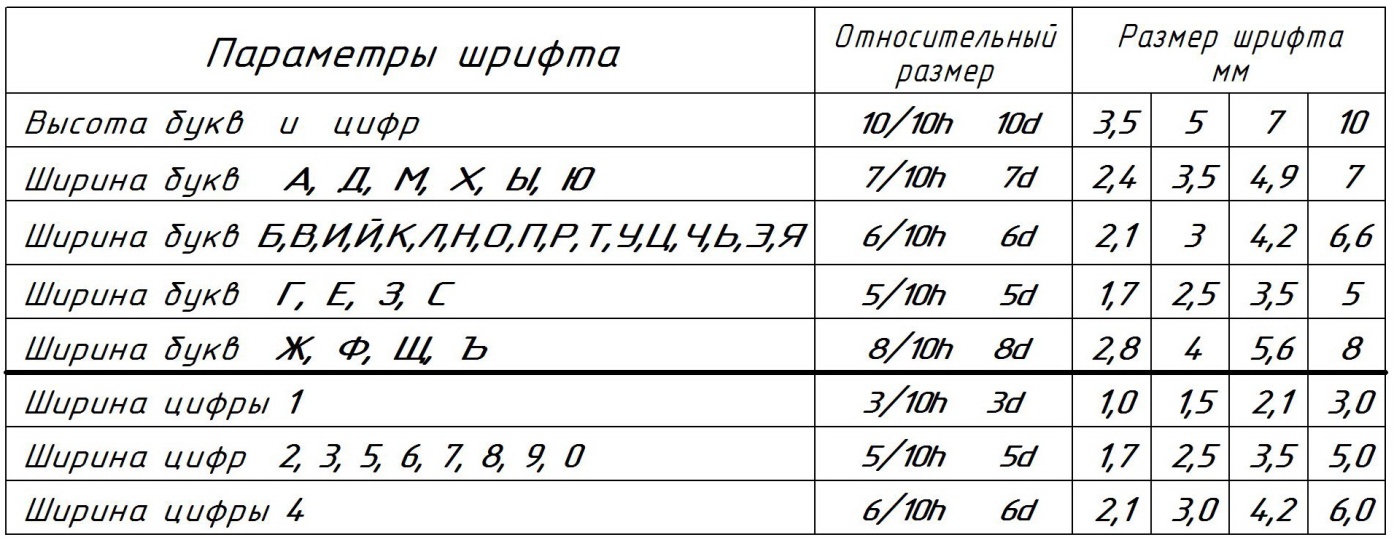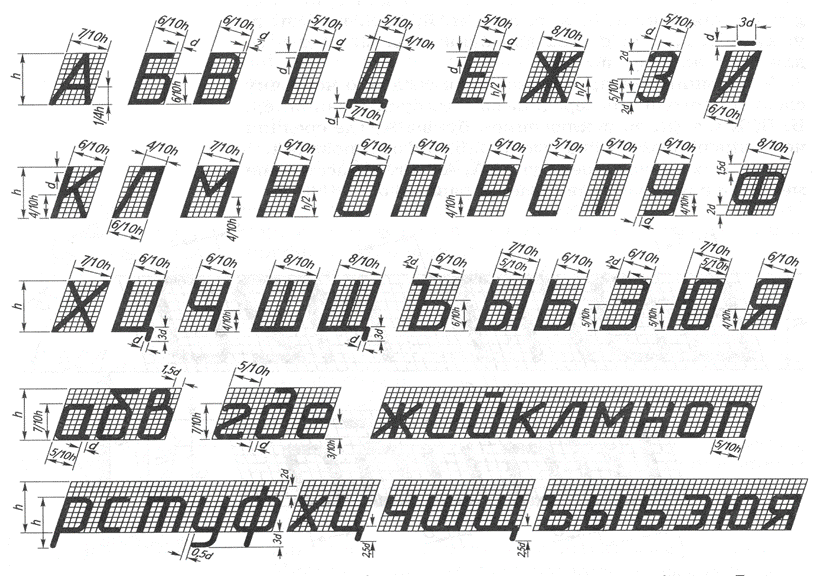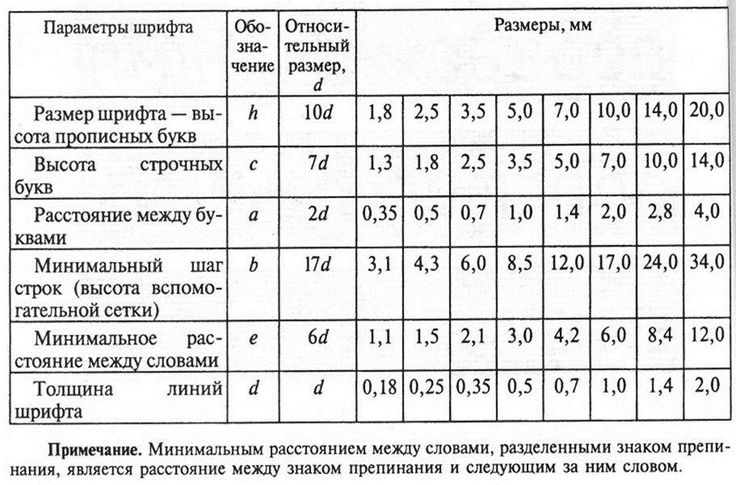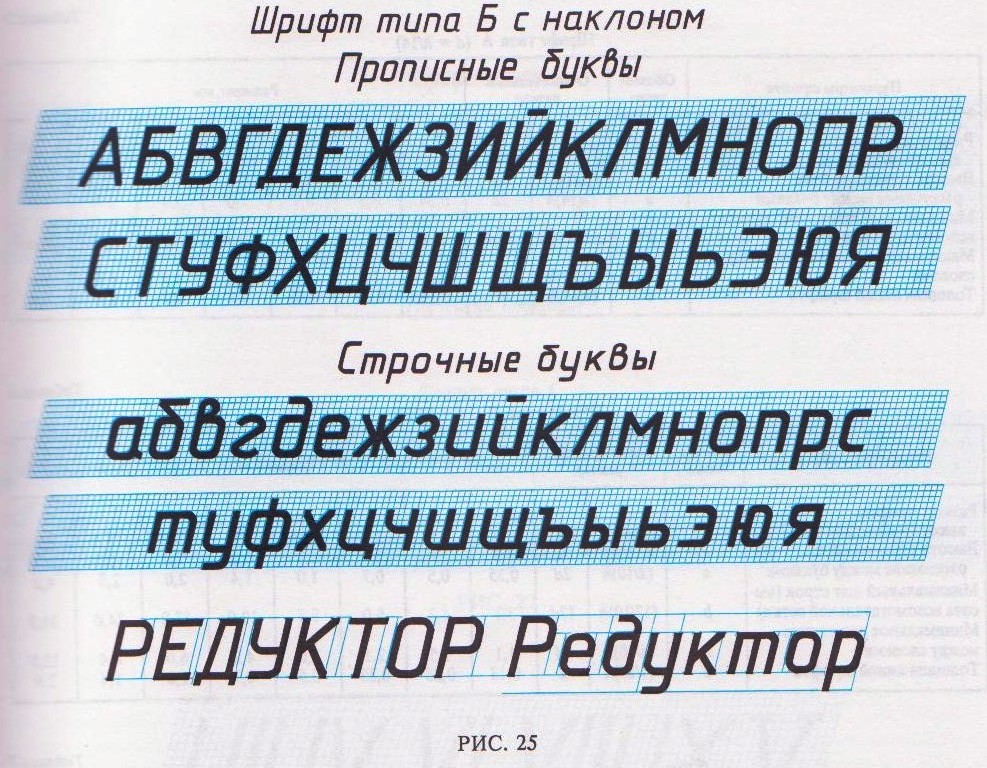
На чертежах и схемах кроме размерных чисел наносят различные надписи как в графах основной надписи (угловом штампе), так и на поле чертежа — надписи с обозначением изображений, а также надписи, относящиеся к отдельным элементам изображаемого изделия или здания. Надписи должны быть ясными и четкими.
Чертежные шрифты.
ГОСТ 2.304—81* устанавливает шрифты для надписей, наносимых на чертежах и технических документах всех отраслей промышленности и строительства. Чертежные шрифты характеризуются простотой конструкции букв, цифр и знаков. Для лучшего восприятия конструкции шрифта его построение показано на вспомогательной сетке (рис.1 а, б), шаг линий которой зависит от толщины линий шрифта. Наклон букв и цифр данного шрифта к основанию строки равен примерно 75°.
Рис.1. Чертежный шрифт с наклоном (тип Б): а — прописные буквы, б — строчные буквы, в — арабские цифры
Размер шрифта характеризуется высотой h прописных букв в миллиметрах (см таблицу).
Таблица Размеры букв и цифр чертежного шрифта типа Б по ГОСТ 2.304-81*
Параметры шрифта | Обозна- чение | Относительный размер | Размеры, мм |
Размер шрифта: — высота прописных букв — высота строчных букв | h с | (10/10)h 10d (7/10)h 7d | 2,5 3,5 5 7 10 14 20 1,8 2,5 3,5 5 7 10 14 |
Расстояние между буквами | а | (2/10)h 2d | 0,5 0,7 1 1,4 2 2,8 4 |
Минимальный шаг строк | b | (17/10)h 17 | 4,3 6 8,5 12 17 24 34 |
Минимальное расстояние между словами | е | (6/10)h 6d | 1,5 2,1 3 4,2 6 8,4 12 |
Толщина линий шрифта | d | (1/10)h d | 0,25 0,35 0,5 0,7 1 1,4 2 |
П р и м е ч а н и е: g -наибольшая ширина буквы, g=6/10h
Установлены следующие размеры шрифта: 2,5; 3,5; 5; 7; 10; 14; 20; 28; 40.
Параметры шрифта зависят от размера шрифта h или от толщины линии шрифта d, равной 1/10h (рис. 2, а).
Высота строчных букв с определяется из отношения их высоты (без отростков h) к размеру шрифта h и составляет с = 7/10h.
Ширина большинства прописных букв равна б/10h (6d). Ширина букв А, Д, М, X, Ы, Ю— 7/10h (7d), а букв Ж, Ф, Щ, Ъ — 8/10d (8d).
Ширина строчных букв и арабских цифр, кроме цифры 1, составляет 5/10h (5d). В 16 случаях конструкция строчных букв повторяет прописные.
Рис.2. Основные типы шрифта и параметры в конструкции букв:
а — шрифт с наклоном (тип Б), б — без наклона (тип Б), в — построение шрифта по вспомогательной сетке, г — построение шрифта с толщиной линий, равной 1/14 высоты прописных букв (тип А)
Скругленные участки прописных букв выполняют в пределах двух толщин (2d) линий шрифта.
Расстояние а между буквами, соседние линии которых не параллельны между собой (например, ГА, AT), может быть уменьшено наполовину, т.
е. на толщину d линии шрифта. Цифру 1 размещают на расстоянии от смежных цифр и букв, равном 2/10h. На рис. 1в дан вариант выполнения цифры 3.
Минимальным расстоянием между словами е, разделенными знаком препинания, является расстояние между знаком препинания и следующим за ним словом. Минимальный шаг строк b, или расстояние между основаниями строк, составляет 17/10h. Таким образом, величина промежутка между строками прописных букв должна быть не менее высоты строчных букв — 7/10h.
При выполнении надписей применяют также чертежный шрифт без наклона (рис. 2, б), имеющий те же размеры и параметры, что и шрифт с наклоном.
ГОСТ 2.304—81* устанавливает еще два чертежных шрифта — с наклоном и без наклона — таких же размеров, но другого типа (рис, 2, в, г), в которых толщина линии шрифта d составляет 1/14h.
Выполнение надписей.
Прежде чем приступить к выполнению надписи, надо хорошо изучить конструкцию букв и цифр шрифта, которым будет исполнена надпись.
При выполнении надписей между двумя параллельными линиями, проведенными на расстоянии, которое соответствует высоте прописных букв, посередине можно провести еще одну линию (рис, 3, а). В большинстве случаев в конструкции букв средние горизонтальные участки линий проводят выше середины высоты прописных букв и цифр. Надписи, заголовки могут состоять только из прописных (заглавных) букв или из прописных и строчных букв (рис. 3, б).
Рис.3. Параметры шрифта (тип Б) (а) и приемы выполнения надписей (б)
При выполнении надписи определяют место для нее и задаются размером шрифта. После этого, если надпись крупная, т. е. высота букв больше 7 мм, необходимо:
— на отведенном для надписи месте провести две параллельные линии на расстоянии, соответствующем высоте букв;
— от начала надписи разметить по масштабной линейке ширину всех букв, расстояние между ними и разрыв между словами;
— через полученные точки разбивки провести параллельные прямые под углом, соответствующим углу наклона шрифта;
— в полученные четырехугольники вписать соответствующие буквы.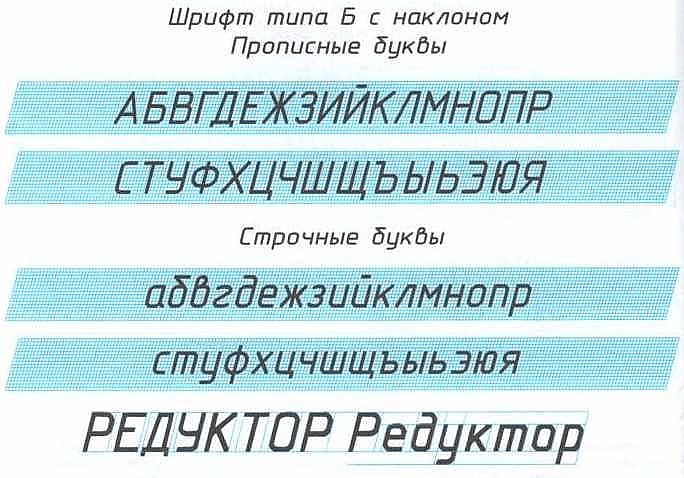
Указанный порядок выполнения надписей рекомендуется как для крупных, так и для мелких надписей. В дальнейшем, когда шрифт будет хорошо изучен, при выполнении мелких надписей можно не строить четырехугольники для каждой буквы и цифры, а провести ряд произвольных штрихов под углом, принятым для данного шрифта. Эти штрихи помогут выдержать одинаковый наклон букв и цифр в надписи. Овладев в совершенстве шрифтом, можно не наносить вспомогательные штрихи, однако две параллельные линии, устанавливающие высоту надписи, проводить надо обязательно. Хорошо изучив конструкции букв и цифр, можно при выполнении надписей ширину букв и цифр и промежутки между ними брать на глаз, выдерживая соотношения, принятые для шрифта, который используют в надписи. Для некоторых шрифтов существуют трафареты, применение которых облегчает выполнение надписей карандашом. Если надпись делают тушью, то предварительно намечают ее в карандаше, а затем обводят тушью.
Таким образом, чтобы удовлетворить всем критериям от дизайна до окончательной сборки, чертеж имеет много целей, и высота текста 2,5 мм удовлетворяет этим критериям для чертежей, созданных в САПР. По моему опыту, все, что меньше 2,5 мм, может вызвать проблемы с четкостью представления и использования.
Я бы стандартизировал высоту текста 2,5 мм.
От Гордона Виттенберга: В настоящее время мы используем стандарт 3/32 дюйма (2,38 мм). Для объема информации, который требуется на многих компоновочных чертежах, 1/8 дюйма (3,175 мм) — это слишком много.